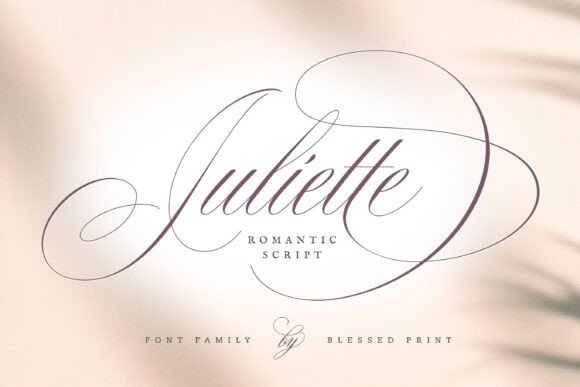
Juliette
Việc tìm kiếm các thành phần thiết kế phù hợp có thể là một thách thức, nhưng Juliette cung cấp một bộ sưu tập đặc biệt giúp nâng tầm công việc của bạn ngay lập tức.
Được chế tác với độ chính xác cao, Juliette cung cấp các vector sạch, kiểu chữ mượt mà và giấy phép thương mại để bạn yên tâm.